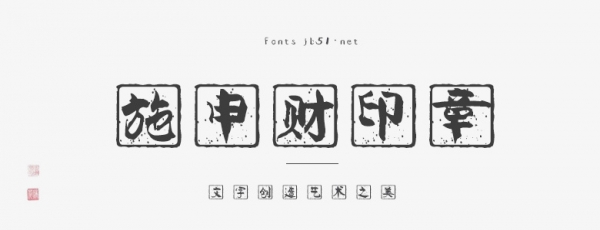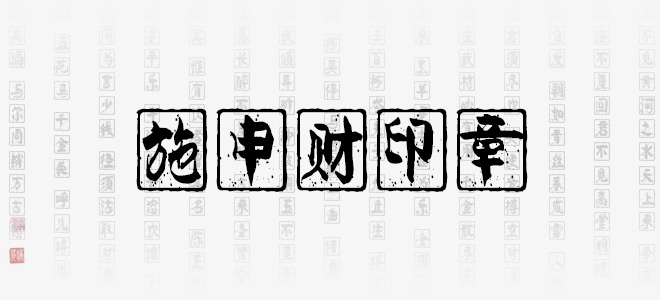
施申財(cái)印章是一款自帶有印章邊框、底色效果的書法藝術(shù)字體,字體線條粗細(xì)適中,筆畫隨性,結(jié)構(gòu)灑脫自在,具有很好的視覺感,適合于文化類的宣傳設(shè)計(jì)、商業(yè)類品牌的廣告和產(chǎn)品包裝設(shè)計(jì)以及個(gè)性化文字排版等較多場(chǎng)景。
施申財(cái)印章